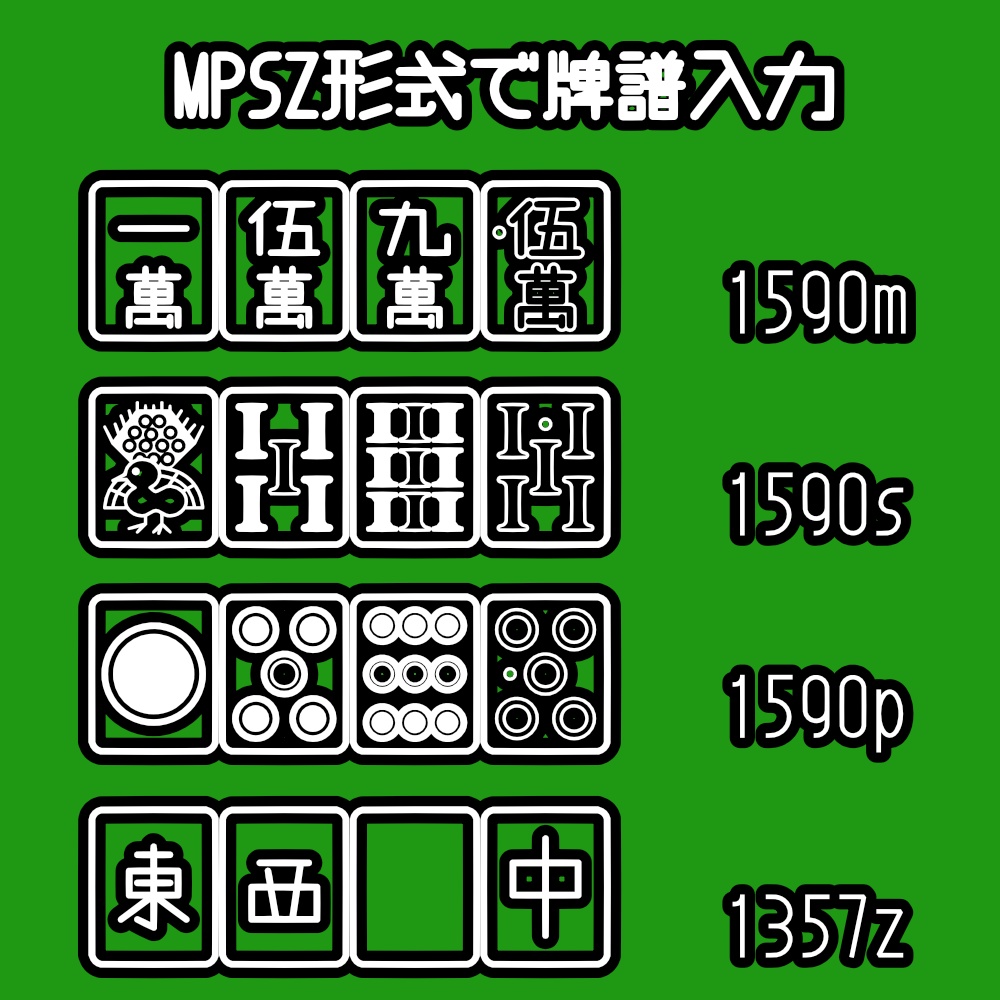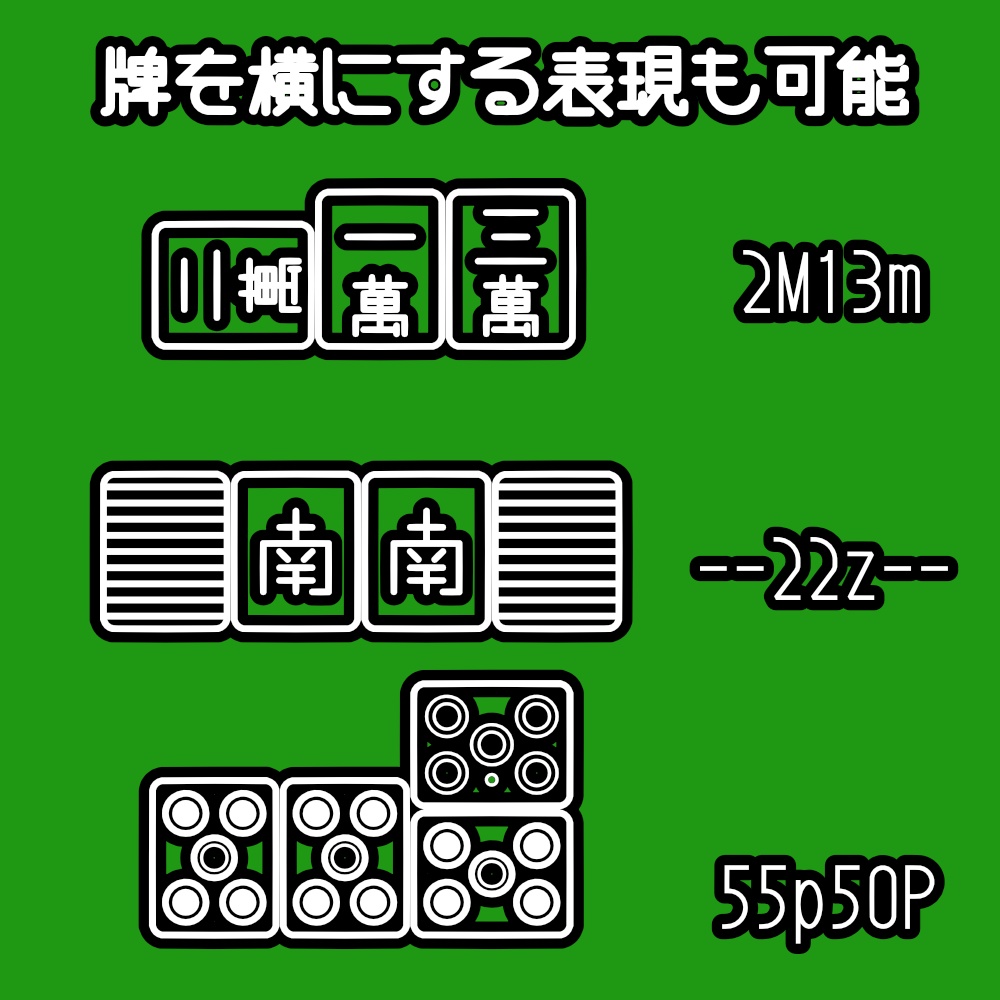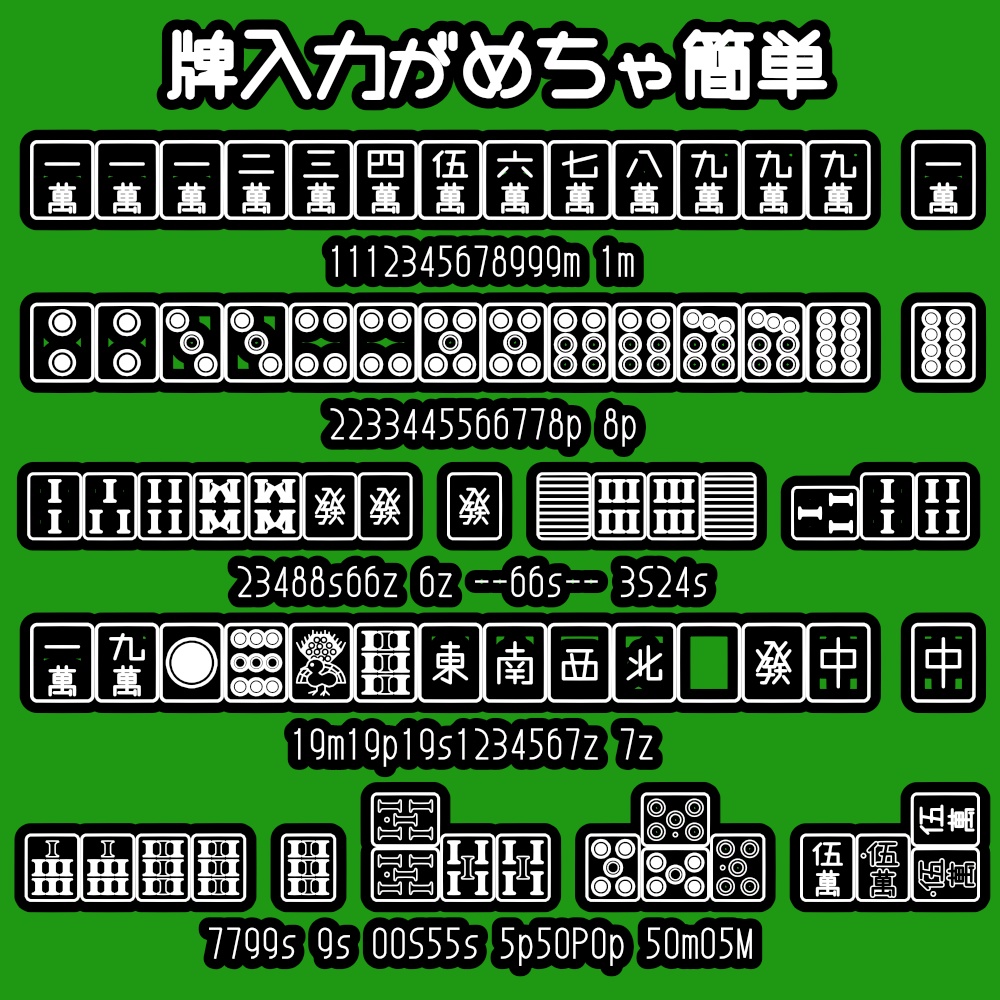
フォント MahjongMPSZ
麻雀牌のフォントです。 タイポグラフィ(OpenType機能)の欧文合字(liga)と文脈依存の異体字(calt)を使用する事で 麻雀の牌譜表現方法であるMPSZ形式による入力が可能となっており、作業効率が大幅に向上します。 カラーフォント版もあります https://torisippo.booth.pm/items/7918778
MPSZ形式(牌番号[0-9]と牌種記号[m,p,s,z])で文字入力すると、その内容に応じた麻雀牌が表示されます。 0m-9m:萬子 0は赤5 0s-9s:索子 0は赤5 0p-9p:筒子 0は赤5 1z-7z:東南西北白發中 数字を続けて入力すると、前文字の牌種を引き継ぎます。 1235m:1萬2萬3萬5萬 1127z:東東南中 数字の連続入力文字数には14文字の制限があります。 あと、ソフトウェアによっては正しく表示されない場合があります。 例) affinity Designer 2.5では、連続した数字が部分的に変換されないことがあります 牌を横に倒す表現も可能です。これはMPSZ形式に定義されていない独自方式です。 牌番号(0-9)と大文字の牌種記号(M,P,S,Z)を入力すると、牌を横に表示します。 牌番号(0-9)を2回と大文字の牌種記号(M,P,S,Z)を入力すると、牌を横に表示し重ねます(ゾロ目、05、50のみ有効)。 --と入力すると、牌を裏側にして表示します。 これらは数字を続けて入力しても、前文字の牌種を引き継ぎません。 横に2段重ねた文字はアセントより上に突き出します。 アセントより突き出るものを作画しないソフトウェアでは正しく表示されない場合があります。 例) OBS 30.2.2 の ソース[テキスト(GDI+)](1行目を空行にしてエリアを作ると表示されます) UNICODEには麻雀記号の割り当て(1F000~1F02F)がありますが、本フォントでは使用していません。